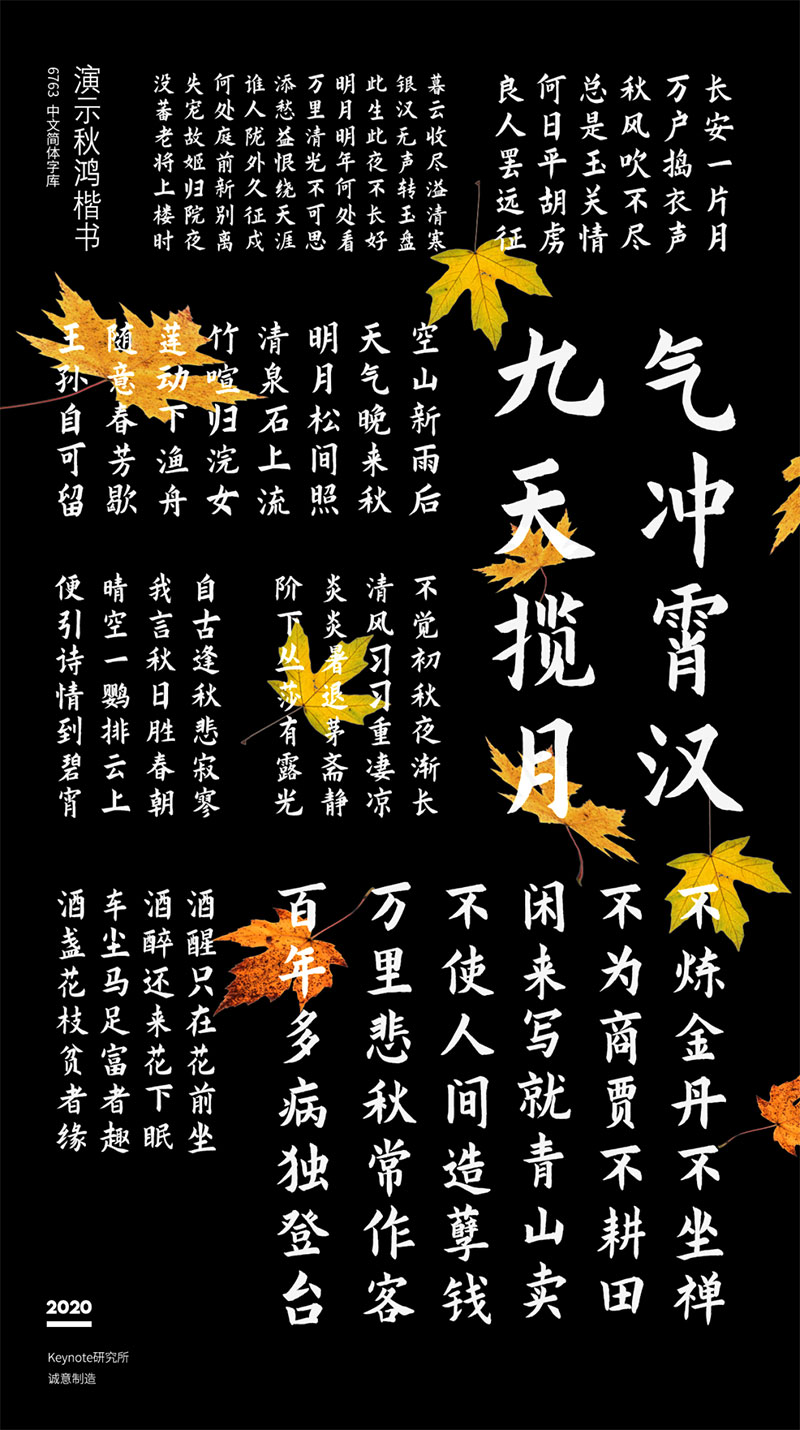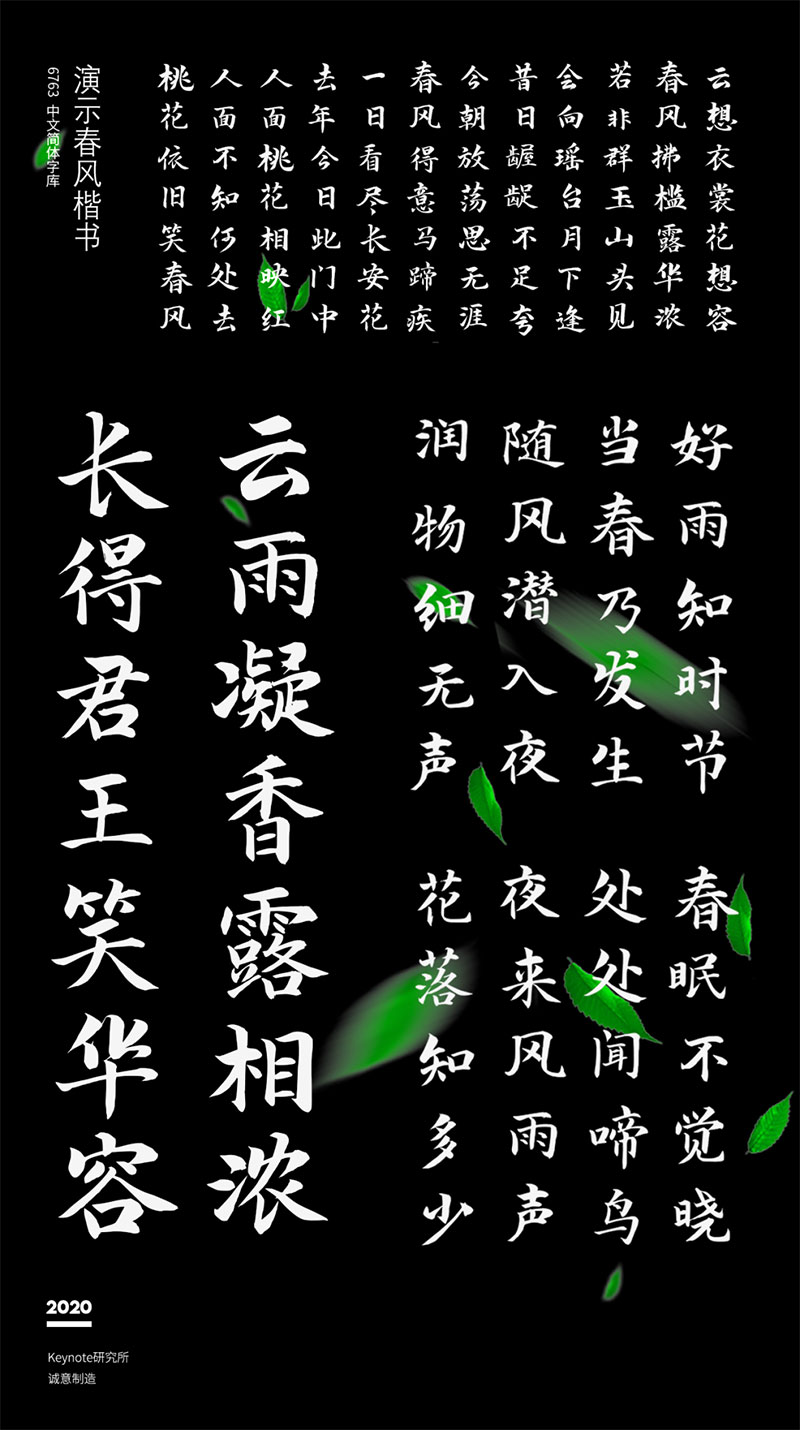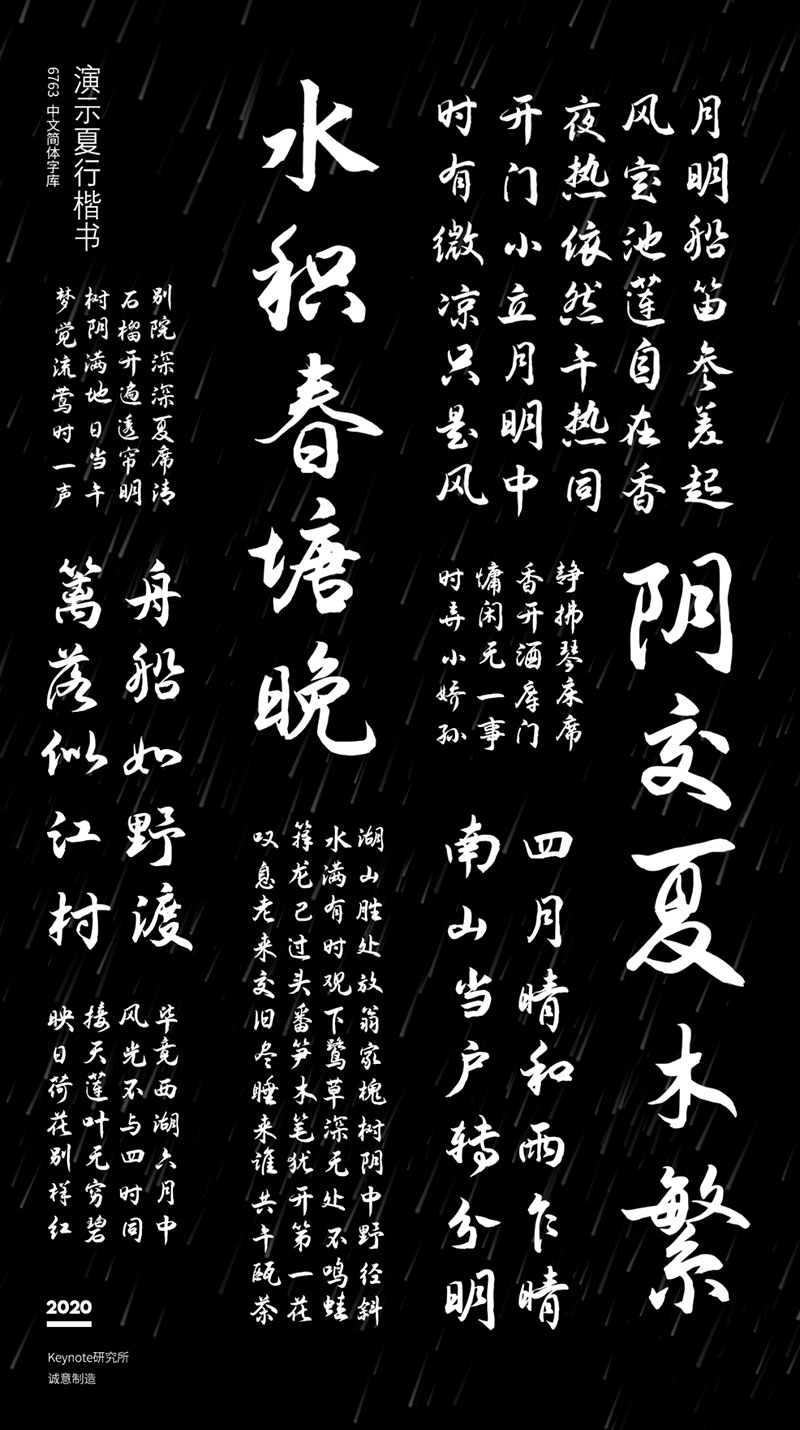
3款演示可商用书法字体
三款字分别为:演示春风楷、演示夏行楷、演示秋鸿楷,由Keynote研究所的人生哥进行半自动流程字稿制作,并向全社会发布免费可商用。
演示春风楷
字稿作者:徐占海
1983年入伍,军人出身丨辽宁人丨每日笔耕不辍
演示夏行楷
中国漓江书画艺术家协会理事丨北京中国书画研究院研究员丨中国民族硬笔书法家协会会员丨中国楹联学会会员丨黑龙江楹联家协会会员丨高级政工师,已退休
演示秋鸿楷
字稿作者:叶运鹏
高中教师丨辽宁人丨98年加入农民书画家协会